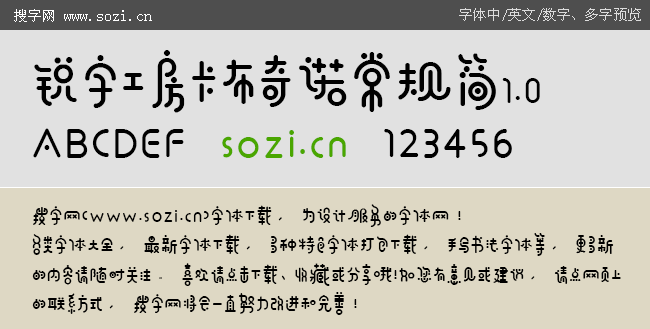
銳字工房卡布奇諾常規(guī)簡
搜字網(wǎng)提供一款非常藝術(shù)的銳字工房卡布奇諾常規(guī)簡下載,銳字工房卡布奇諾常規(guī)簡是一款字形呈卡通效果的銳字工房字體,該字體極具藝術(shù)感,非常有趣,適用于包裝印刷、廣告設(shè)計、平面設(shè)計、書籍報紙等領(lǐng)域。
- 風(fēng)格類別: 海報POP體